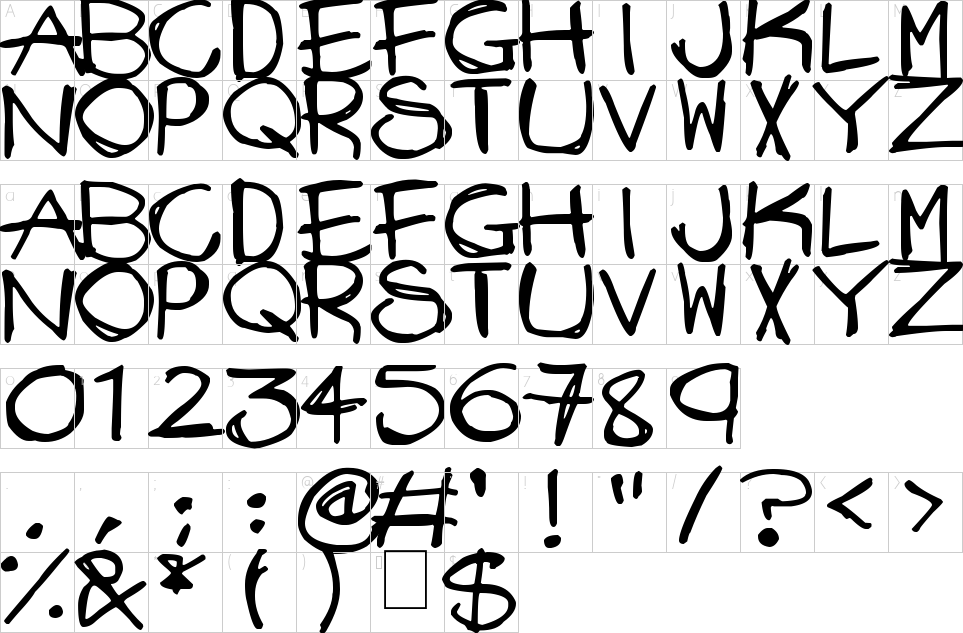
Mad Stick Brush Font | 1001 Free Fonts – Fonte Grátis
A fonte Mad Stick Brush é uma escolha perfeita para designers que buscam uma gráfica e moderna opção para suas criações. Desenvolvida por Darrell Flood, esta fonte vem como um brush digital, oferecendo um estilo elegante e fácil de se trabalhar. Se você está procurando por uma fonte que combina os elementos de um desenho à mão com a precisão da digitalização, Mad Stick Brush será uma ótima escolha. Com um design único e atraente, esta fonte adquire o papel, estampas e textos digitais, tornando-a versátil para qualquer projeto. Com um download de mais de 1.910 vezes, a Mad Stick Brush é uma escolha popular entre designers de todo o mundo. Aproveite para adicionar um toque personalizado e moderno a seus projetos com essa fonte de qualidade.